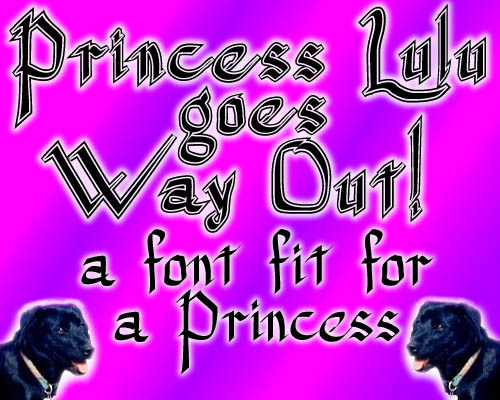
Princess Lulu di S. Roland Frantz è un font gratuito in stile blackletter scritto a mano, che evoca l'atmosfera dei libri di fiabe di un tempo. Le lettere uniscono tratti affilati a curve angolari e a un dinamismo calligrafico: il risultato è più vicino al titolo di una fiaba che a una formale riscoperta gotica.
È ideale per copertine di libri, packaging artigianale, inviti a eventi, titoli di poster e branding a tema, dove un tocco di romanticismo medievale aiuta a creare la giusta atmosfera. Essendo un font gratuito, è perfetto anche per titoli, brevi citazioni o iniziali in stile monogramma, poiché le sue forme appuntite e le diagonali vivaci colpiscono immediatamente l'attenzione.